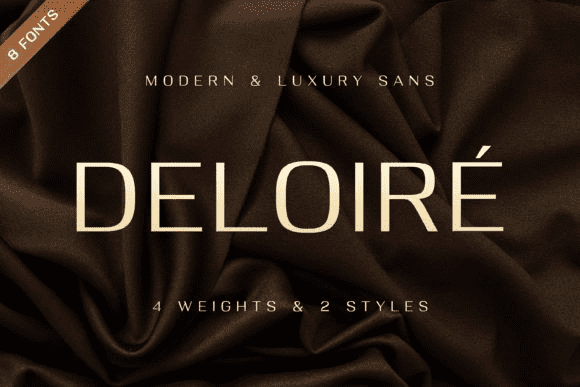
Название: Deloire Font
Делуаре - классический шрифт без засечек.
Он добавит невероятно современный штрих к вашему дизайну.
Добавьте этот красивый шрифт к каждой вашей творческой идее и заметьте, как он выделяет их!